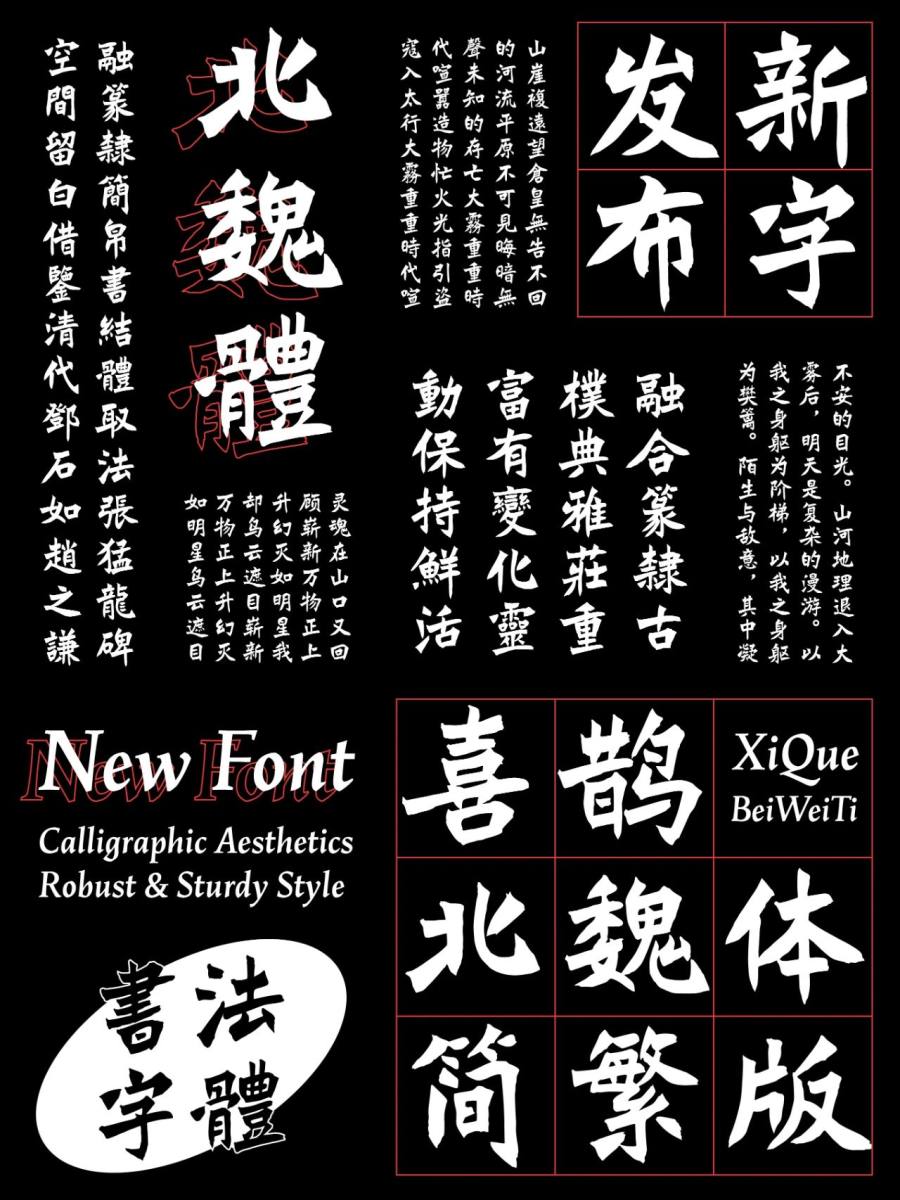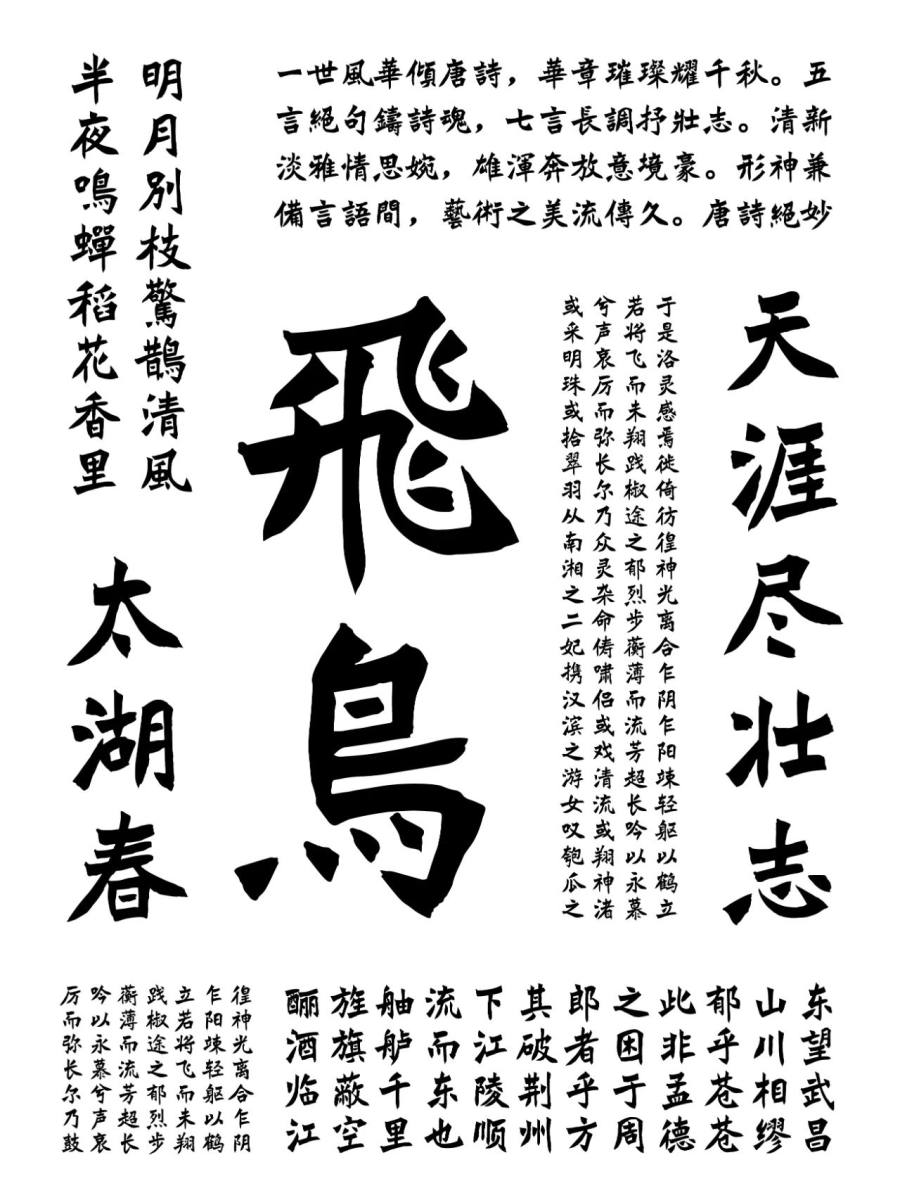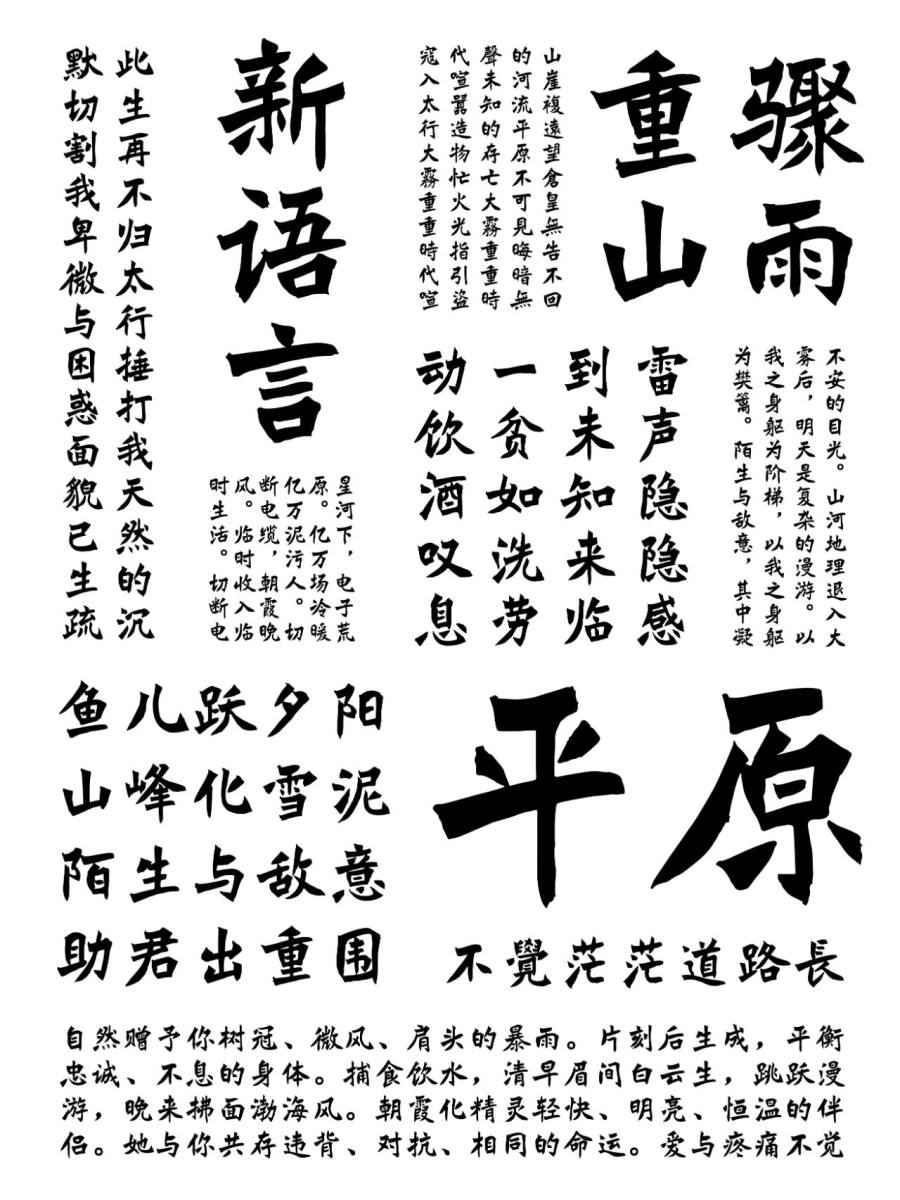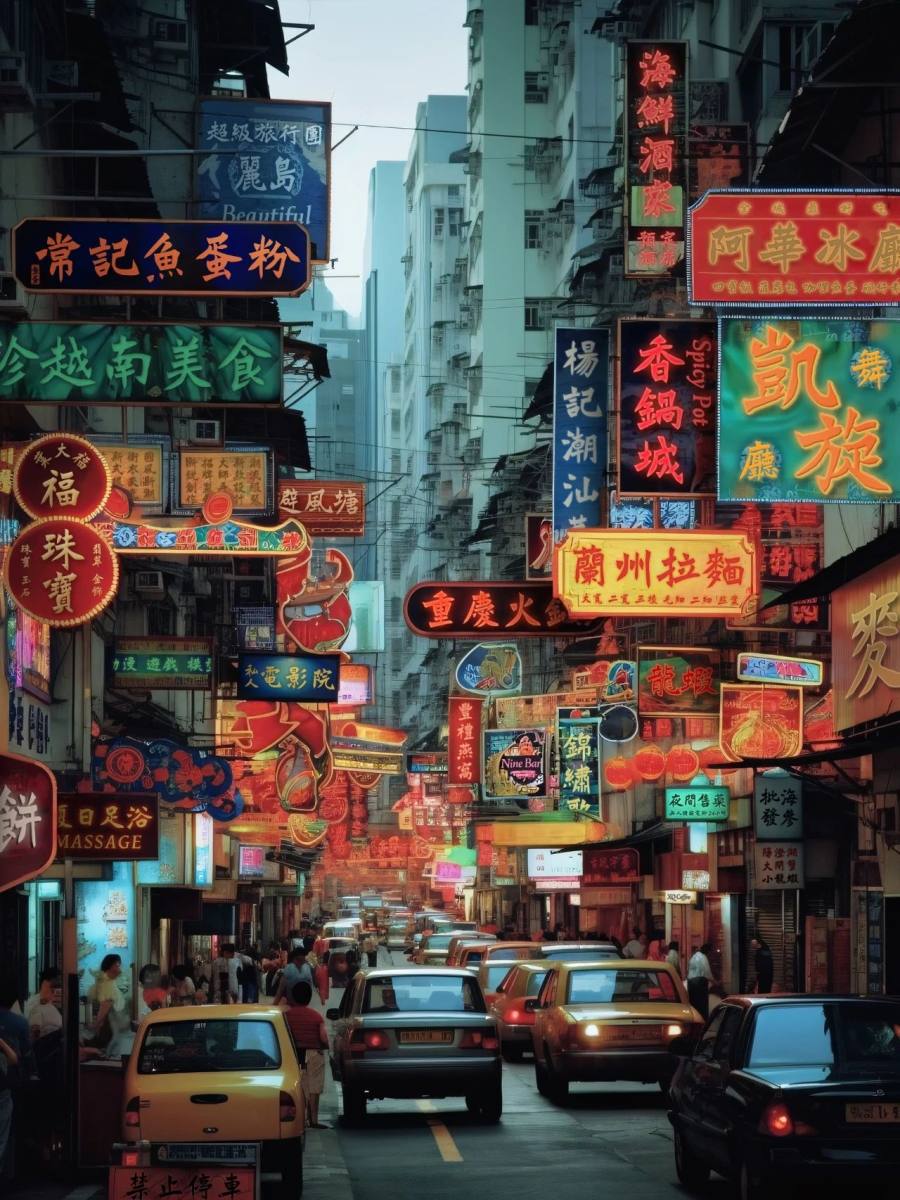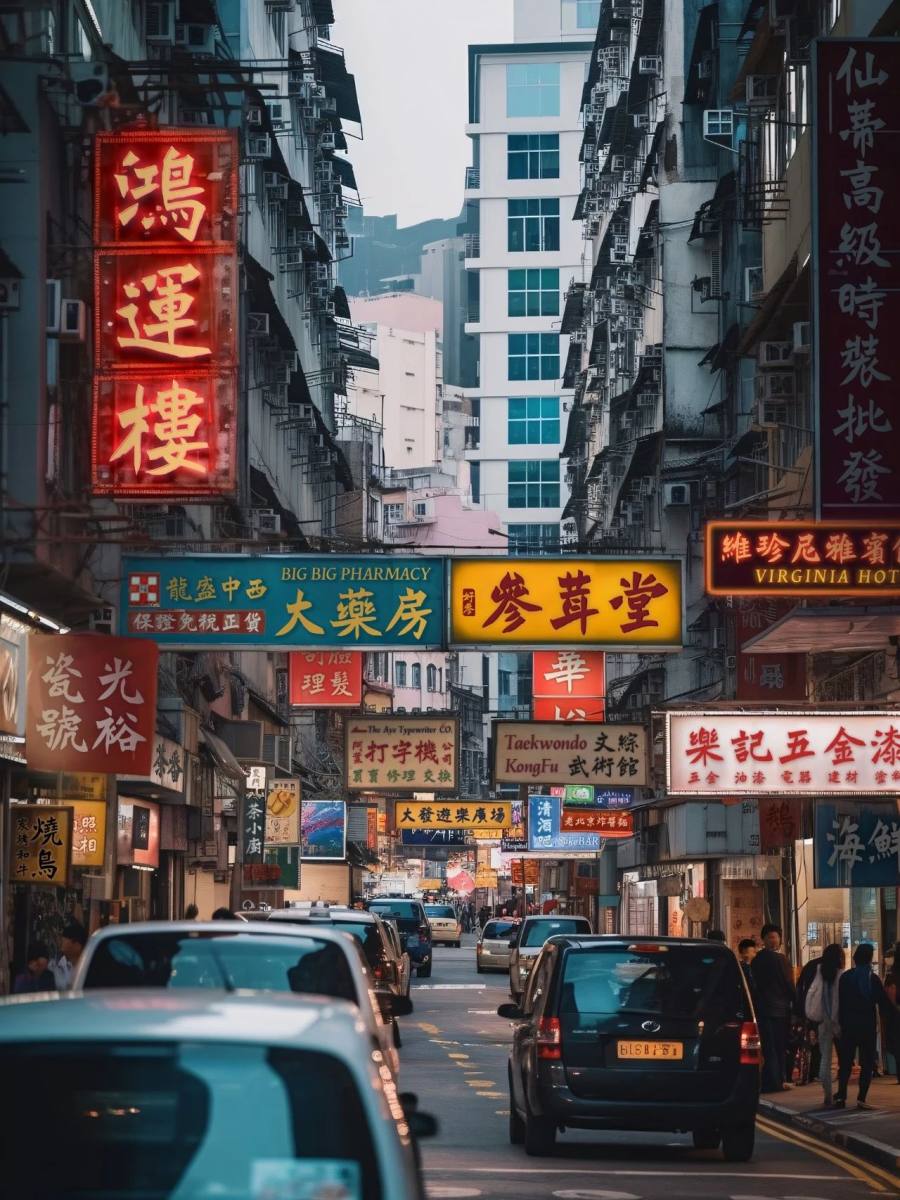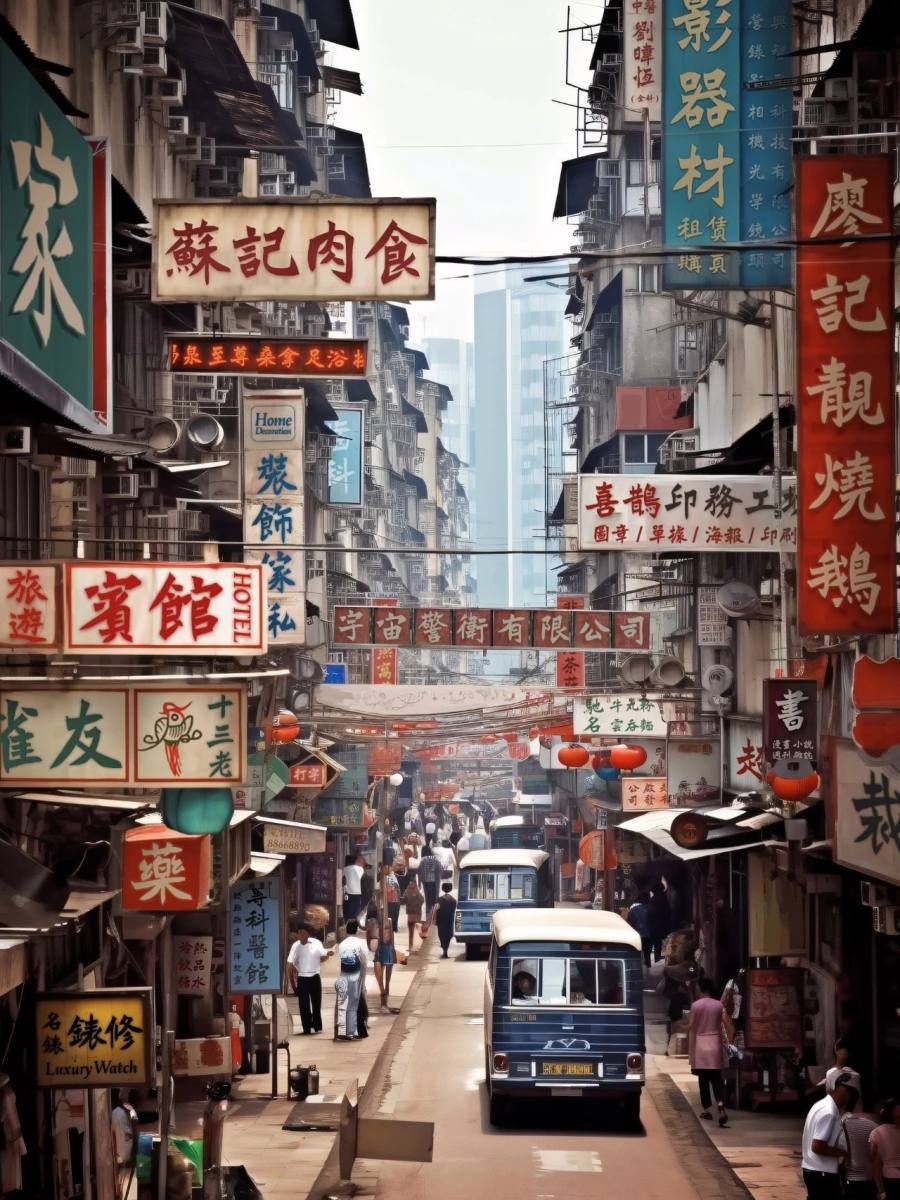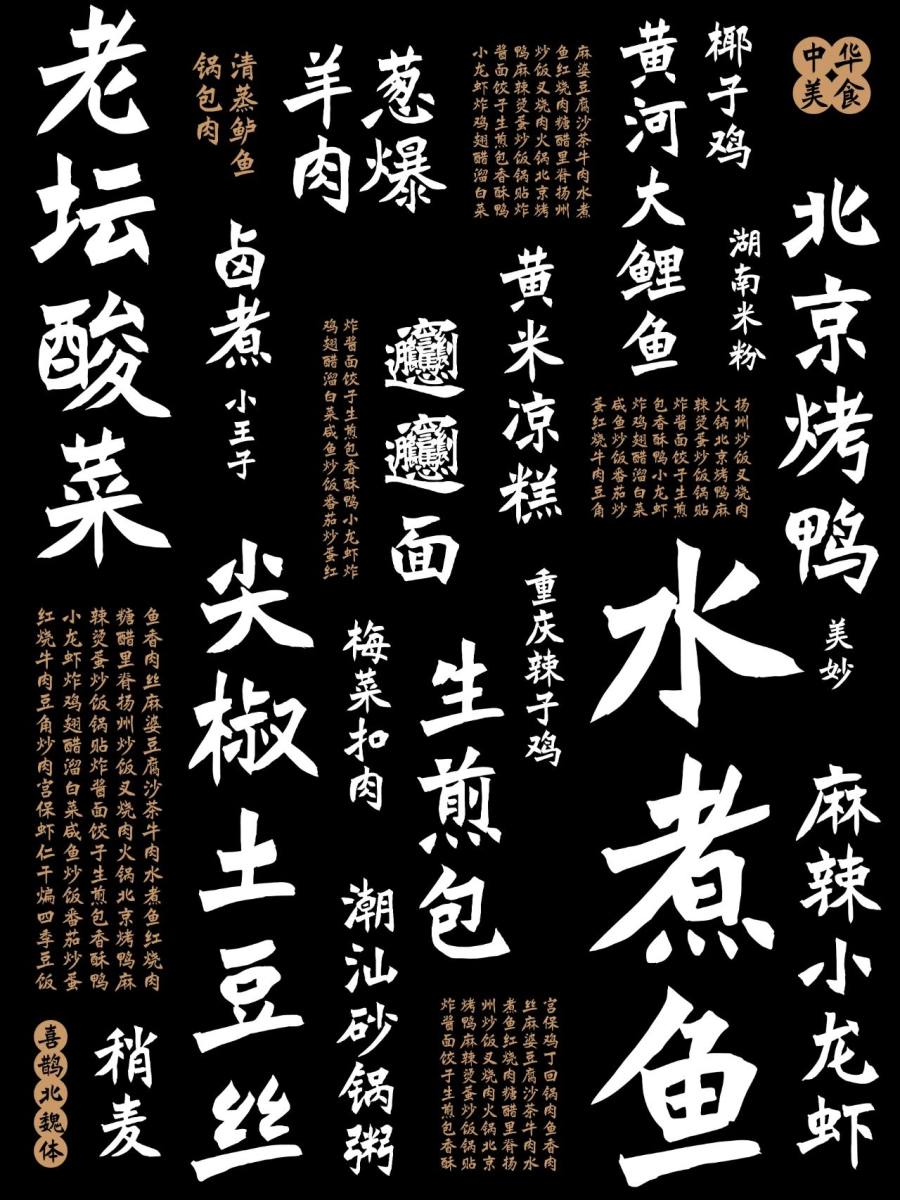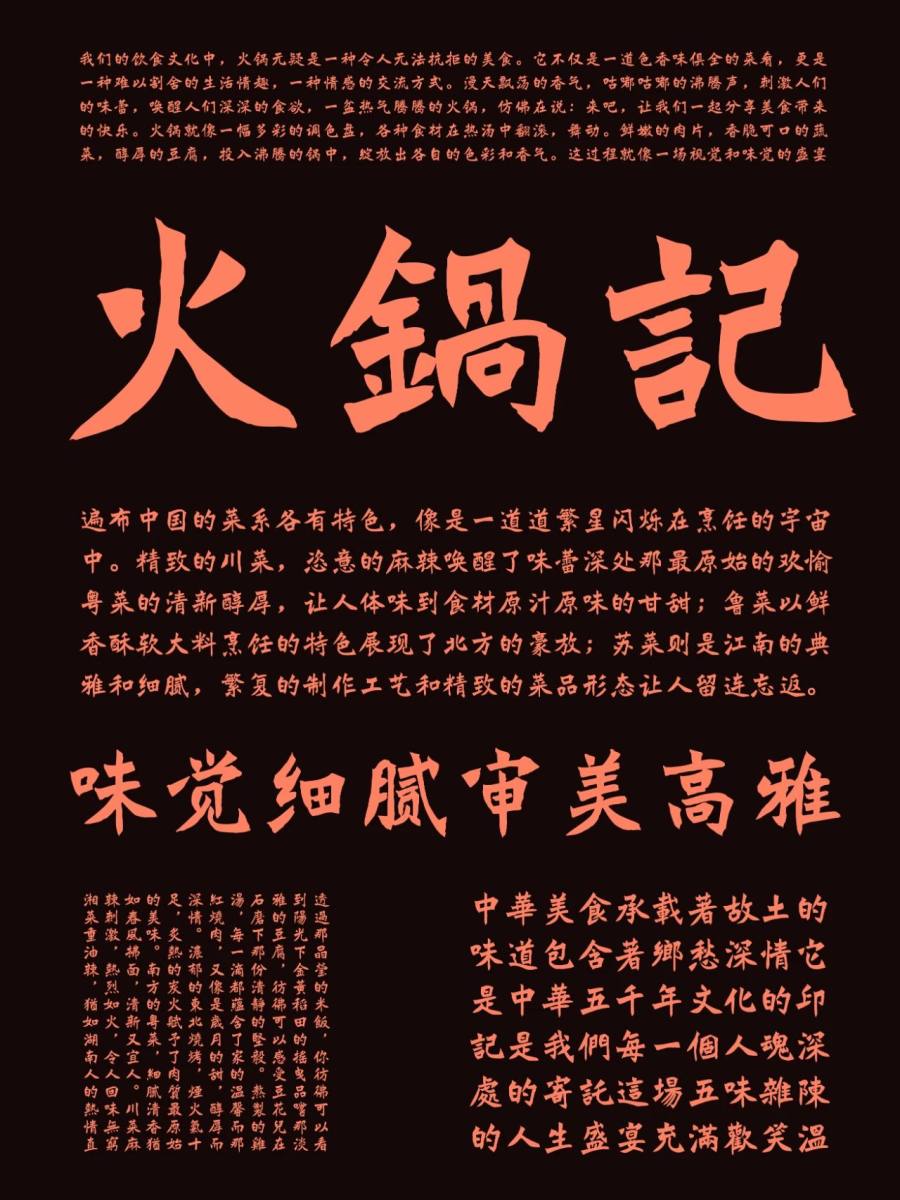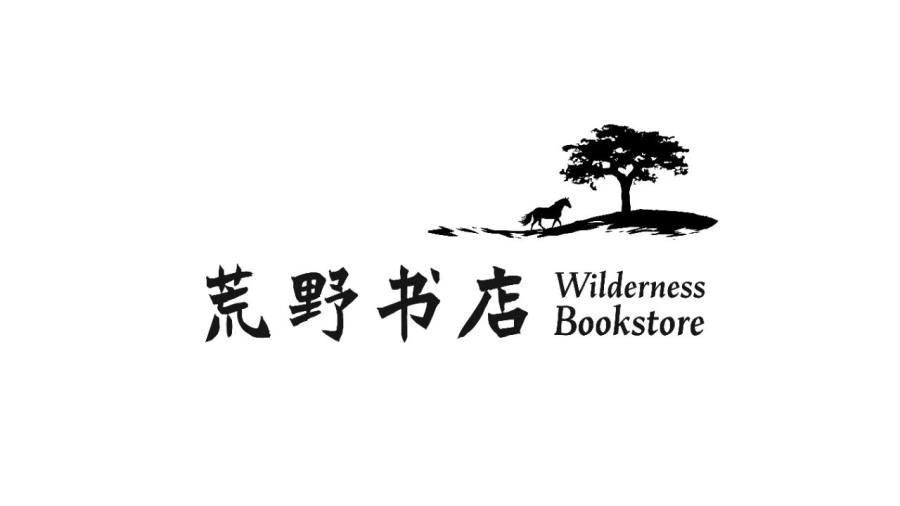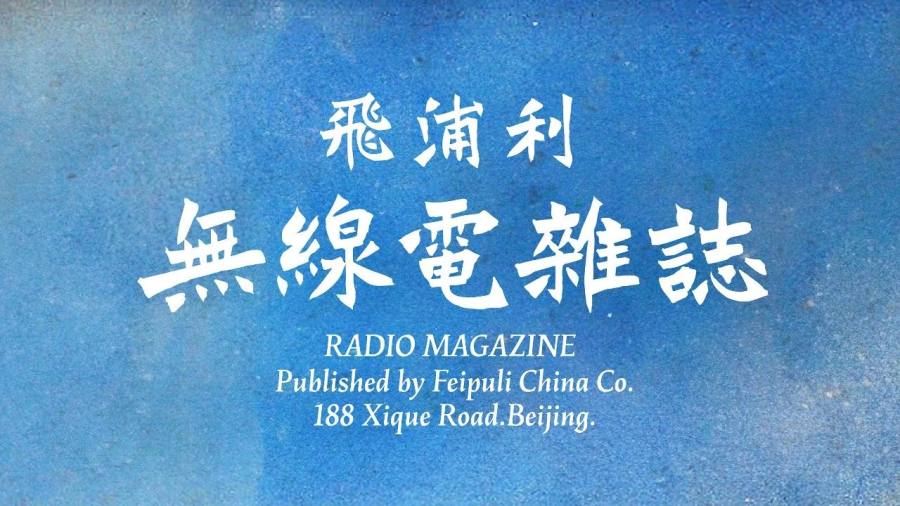
喜鹊北魏体以北魏《张猛龙碑》为基础,按北碑例字的标准进行创作。10厘米见方,一纸一字,在书写中逐步建立以题匾榜书为应用场景的理念,用笔融汇篆隶简帛,追求书写感;结体取法原碑,空间留白借鉴清代邓石如、赵之谦隶书、楷书,进行了篆书化处理。反复书写调整,直至完全统一。
喜鹊北魏体展示
北魏体字字如拳,雄浑有力,适用于题匾榜书等环境。
满城都是北魏体,效果赞!
北魏体这个书法肌理加上古朴的气质 实在是跟中华美食十分契合,又亲切,于是又排版一波美食文字
用于文字Logo或标题当中的效果:
用于国产影视名字的书写效果展示
西文字体展示:
北魏体用于展览展示、包装设计、封面设计展示